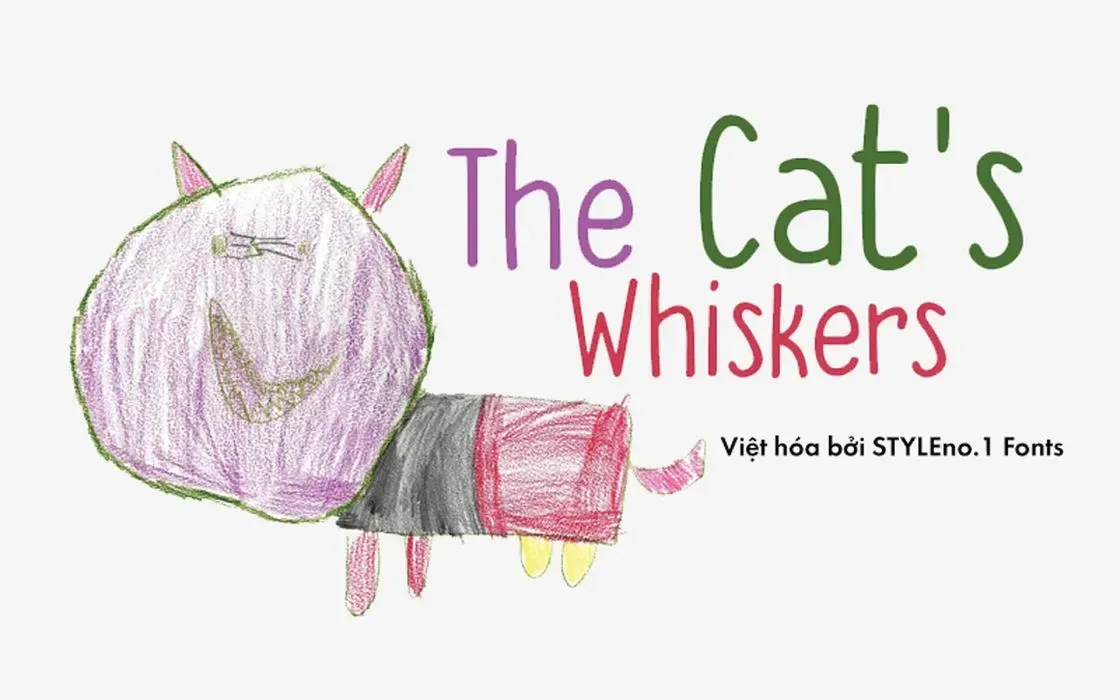
SVN The Cats Whiskers là một font chữ display sans-serif mang phong cách hoạt hình vui nhộn, dễ thương và đầy tinh nghịch. Các ký tự có hình dáng tròn trịa, ngả nghiêng nhẹ, và đường nét được bo mềm, tạo nên cảm giác như bước ra từ những cuốn truyện tranh hoặc hoạt hình thiếu nhi. Từng chữ cái như đang “nhảy múa”, mang đến nguồn năng lượng tích cực và cảm xúc hồn nhiên trong thiết kế.
Font đặc biệt phù hợp cho các ứng dụng như:
– Tiêu đề truyện tranh, poster phim hoạt hình
– Bìa sách thiếu nhi, nhãn vở, bảng tên lớp học
– Thiết kế bao bì đồ chơi, thực phẩm trẻ em, nhãn dán vui nhộn
– Sản phẩm liên quan đến giáo dục sớm, app học chữ cho bé
Font gốc The Cats Whiskers do nhà thiết kế Joanne Marie phát hành, với mục tiêu tạo ra một kiểu chữ mang tính cá nhân hóa cao, đáng yêu và dễ ứng dụng trong các thiết kế thân thiện với trẻ em hoặc các sản phẩm nữ tính, handmade.
Nếu bạn đang tìm một font chữ hoạt hình, đáng yêu và thân thiện với trẻ em, thì SVN The Cats Whiskers là lựa chọn hoàn hảo để truyền tải sự vui tươi, sáng tạo và ngọt ngào trong các thiết kế liên quan đến thiếu nhi, giáo dục và giải trí nhẹ nhàng.